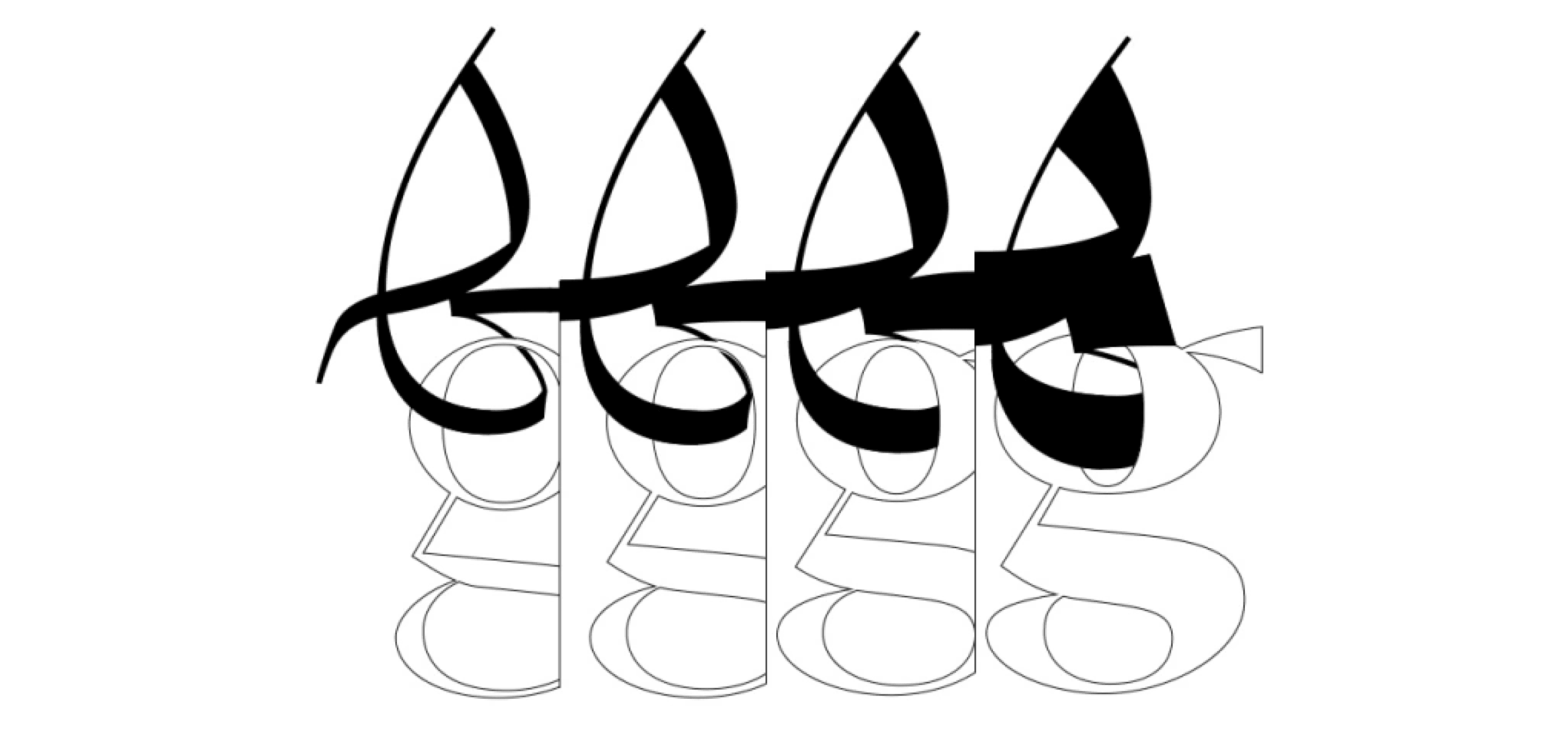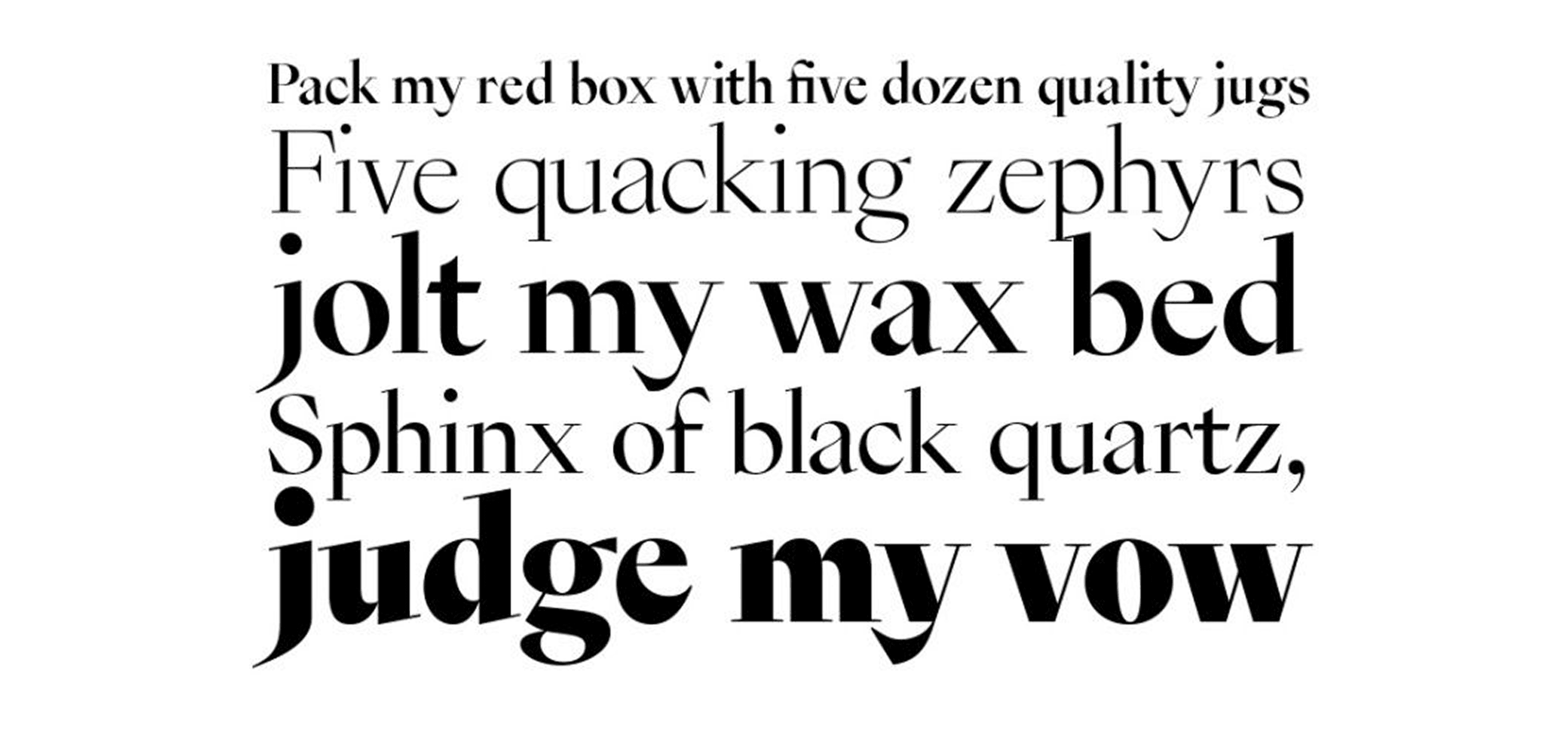
يتميّز 29LT Zein بأسلوب Serif أنيق يعكس طابعًا كلاسيكيًا راقٍ، مع حواف دقيقة وانحناءات متوازنة تمنحه حضورًا فخمًا في العناوين والنصوص الرسمية. مثالي للاستخدام في تصميمات التحرير، المجلات، العلامات التجارية الفاخرة، وأغلفة الكتب.